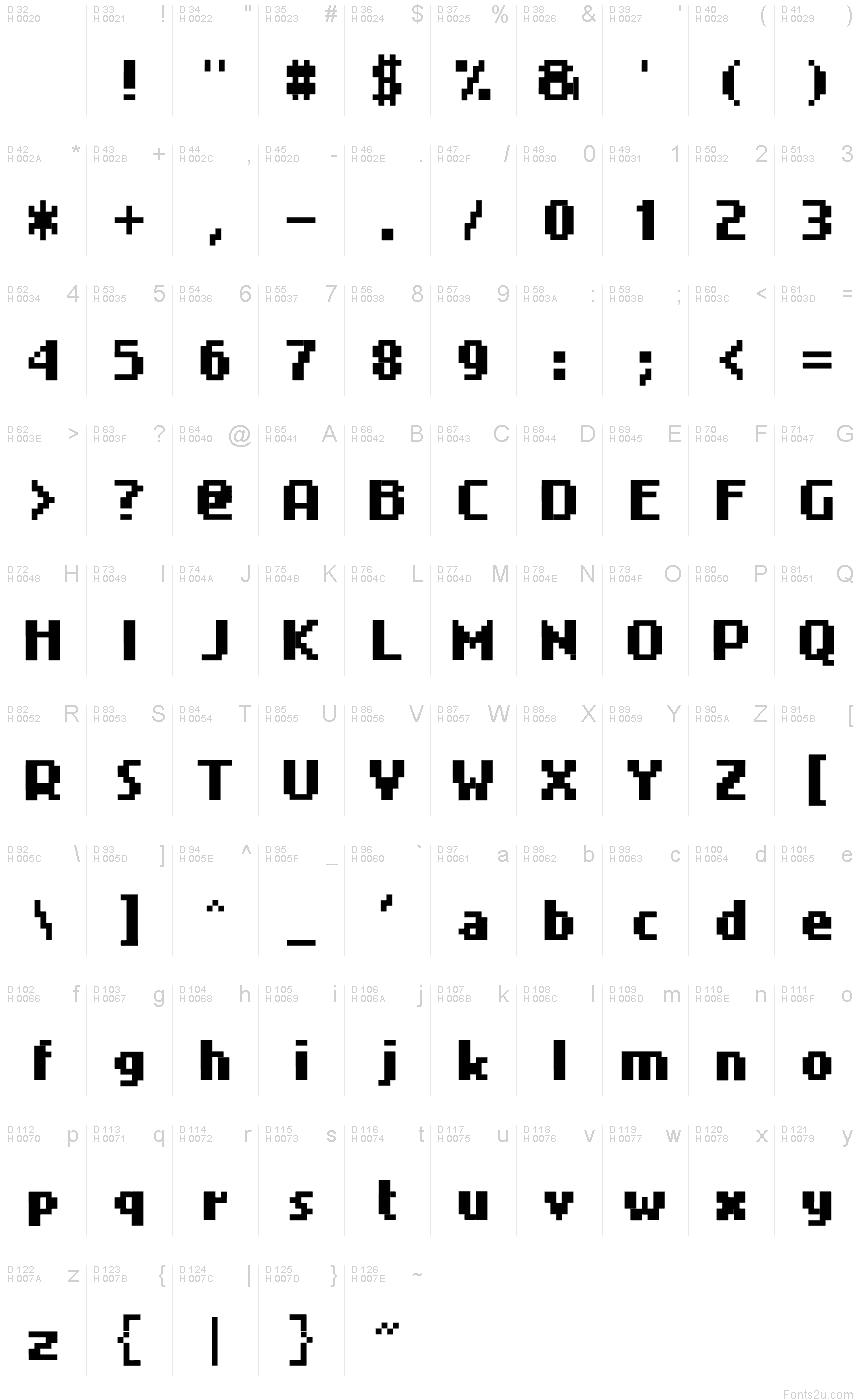
4Mini 字体
4Mini
Astigmatic
Bartek Nowak
4Mini 是一款大胆且具有像素感的位图字体,散发着复古魅力。这款字体由 Bartek Nowak 设计,以其独特的方块美学引人注目,紧凑的结构让人过目难忘。锋利、棱角分明的字形与极小的留白相得益彰,营造出强烈的视觉冲击力,既有怀旧气息,又兼具数字时代的先锋美学。
凭借出色的通用性,这款字体适用于多种设计场景,从低分辨率图形和复古风格界面,到印刷和线上媒体中的大胆排版,都能驾驭自如。其醒目且富有冲击力的风格,是标题、Logo 以及需要即时视觉关注的设计项目的绝佳选择。